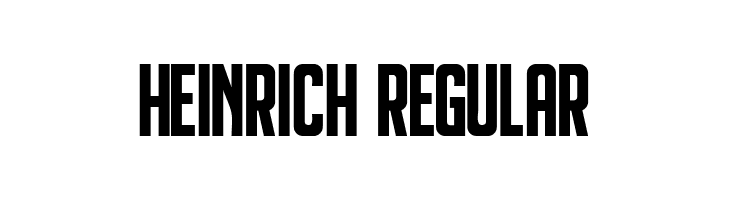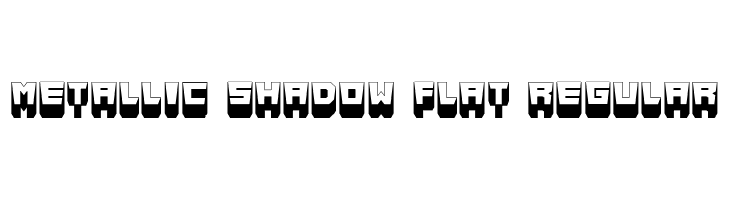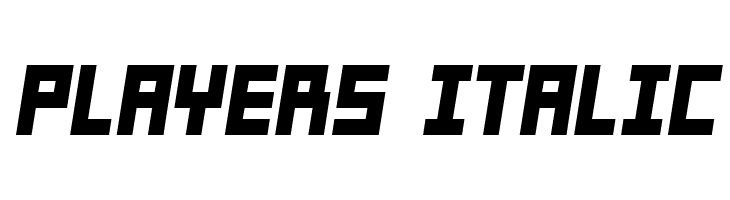
A bold, shadowed font with filled characters for a striking, three-dimensional look.
A bold, condensed font with rounded edges and tight spacing, ideal for impactful headlines.
A bold, italic font with a dynamic and modern style.
A bold, filled, italicized font with a three-dimensional geometric style.
A bold, geometric font with a three-dimensional outline effect.
A bold, three-dimensional block font with a modern, industrial feel.
A bold, three-dimensional font with an italic slant and shadow effect.
A bold, dynamic font with a unique linear pattern and modern industrial feel.
A bold, decorative font with intricate geometric patterns inside each uppercase letter.
A decorative font with characters inside heart shapes pierced by arrows.
现在大家都在用哪些新字体?
流行变化很快,但极简无衬线与个性鲜明的展示体当前更受欢迎, 特别适合移动端内容与现代品牌风格。
有哪些值得尝试的 5 款新字体?
近期热门包括 Impressum Shadow Filled Regular, Impressum Italic, Extradition Filled Italic and Extradition Filled Regular 它们在清晰度与个性之间取得平衡,适用于科技品牌、编辑排版与社媒视觉。